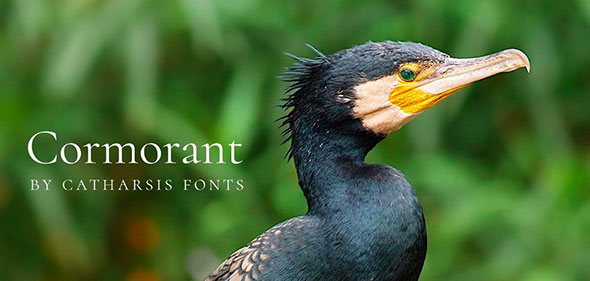
クラシックフリーフォント25選|見出しにも本文にも使える無料の欧文セリフ書体
伝統的・クラシカルな雰囲気のデザインに使える、美しい「無料フォント」をお探しではありませんか。この記事では、セリフ体を中心に、見出しにも本文にも使えるクラシックスタイルの欧文フリーフォントを厳選して紹介します。いずれも可読性が高く、ポスターやロゴ、ブランディング、書籍・Webデザインなど幅広い用途に向いた書体です。掲載しているフォントの多くは、デザイナー本人のページや配布元から無料でダウンロードできます(2026年6月時点)。なお、本記事は2018年公開の内容を最新の状況に合わせて見直したものです。
Butler
Butlerは、Dala FlodaフォントファミリとBodoniフォントファミリからインスピレーションを受けてデザインされたクラシックなフリーフォントです。印刷物とデジタルプロジェクトの両方に適した、モダンなセリフ体です。デザイナーのFabian De Smetによる作品で、公式サイト(fabiandesmet.com)やBehanceから配布されています。
Fakedes
Fakedesは、フォント作家のCyril Mikhailovがデザインした古典的なフォントです。二重線の丸文字セリフフォントで、見出しやロゴに向いています。
Forum
Forumは古典的なローマン体(ローマン・キャピタル)に触発されたフォントです。タイトルや見出しに向いており、フォント作家のDenis Masharovによって丁寧にデザインされています。現在は Google Fonts でも配布されているため、Webフォントとしても使いやすい書体です。
Muchacho
Muchachoは、古典的でありながら風変わりなデザインの大文字フォントです。この書体は、フォント作家のJeff Schreiberによってデザインされました。見出しに使うのがおすすめです。
Poly
Polyは古典的なウェブフォントで、インクトラップと装飾を備えています。垂直方向が強調されたデザインで、Nicolás Silvaによる作品です。
Barbaro
Barbaroは古典的な印象の、美しいフォントです。Iván Núñezによって制作されました。ヴィンテージ感と60年代の雰囲気をまとっており、見出しやロゴ、印刷物やデジタルプロジェクトなどに使用できます。
Le Super Serif
Le Super Serifはヴィンテージかつクラシックスタイルの華麗なフォントです。80以上の合字と特殊な代替文字が用意されています。SuperBruutによるデザインです。
Firefly
Fireflyはクラシックな雰囲気のヴィンテージ・手描き風セリフフォントです。Sean Coadyがデザインしました。プリントデザイン、特にポスターに適しています。
Pelmeshka
Pelmeshkaは、Bodoniフォントファミリの影響を受けた楽しいフォントです。見出し、ロゴ、子ども向けの本などに使えます。Cyril Mikhailovによる作品です。
Fénix
Fénixは、Fernando DíazとTipoType Foundryがデザインした美しい古典フォントです。大きなセリフ(ひげ飾り)と荒々しいストロークを持ちながら、全体としてはエレガントなデザインです。読みやすく多目的で、見出しにも本文にも適しています。
Akura Popo
Akura PopoはTwicolabs Designチームによってデザインされたヴィンテージ感のあるクラシックフォントです。縦長のセリフ体で、荒っぽい見た目が特徴です。読者の注意を引く見出しに向いています。
Molesk
Moleskは、フォント作家のPedro Loboによってデザインされた印象的なフォントです。古典的な書体に触発されたスラブセリフ体で、文字ひとつひとつにかすかな影が付いています。細かな装飾が美しく、見出し、ロゴ、プリントプロジェクトに向いています。なお配布元のページが移動・終了している場合があるため、リンク先が表示されないときはフォント名で再検索してみてください。
Rancho
Ranchoはワイルドウェスト(西部開拓時代)にインスパイアされたクラシックフォントです。Nach Ohによって設計されました。デジタルでも印刷でも、さまざまなプロジェクトに合わせやすい書体です。
Bariol Serif
Bariol SerifはAtipoがデザインした古典的なセリフフォントです。きれいな線と読みやすさを備えたクリーンな書体で、あらゆるデザインの見出しと段落の両方に使えます。
Lovato Light
Lovato Lightは、クラシックな雰囲気の読みやすいフォントです。碑文(インスクリプション)風のレタリングで、ジオメトリックなデザインが特徴です。細字・標準・やや太字・太字・ブラックのスタイルが用意されており、Philatypeによってデザインされました。
Yeseva One
Yeseva Oneは、丸みを帯びたエレガントなクラシックフォントです。Jovanny Lemonadによる作品で、現在は Google Fonts でもSIL Open Font Licenseのもと配布されています(出典: Yeseva One – Google Fonts)。Webフォントとしても扱いやすい書体です。
Luthier
Luthierは、シャープなデザインのクラシックフォントです。コントラストの高いセリフ体で、タイポグラファーのAdrià Gómezが設計しました。4種類のスタイルが用意されているため、さまざまなプロジェクトに使用できます。
Cormorant
Cormorantは、人気のGaramondフォントファミリからインスピレーションを受けたフォントです。Christian Thalmannによって制作され、高解像度・大画面サイズでの表示を前提にデザインされた古典的なディスプレイ書体です。オープンソースで、現在は Google Fonts でもSIL Open Font Licenseのもと配布されています(出典: CatharsisFonts/Cormorant – GitHub)。
Valkyrie
Valkyrieは、フォント作家のHendrick Rolandezがデザインした華麗なフォントです。見出し、ロゴ、ブランディング、印刷物などに使用できます。
Marta